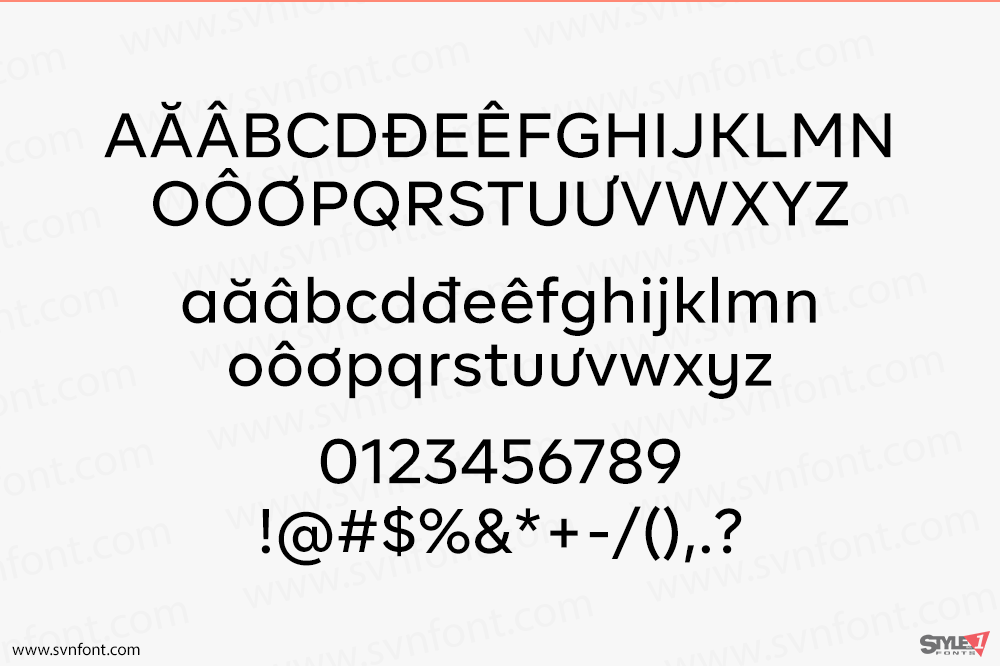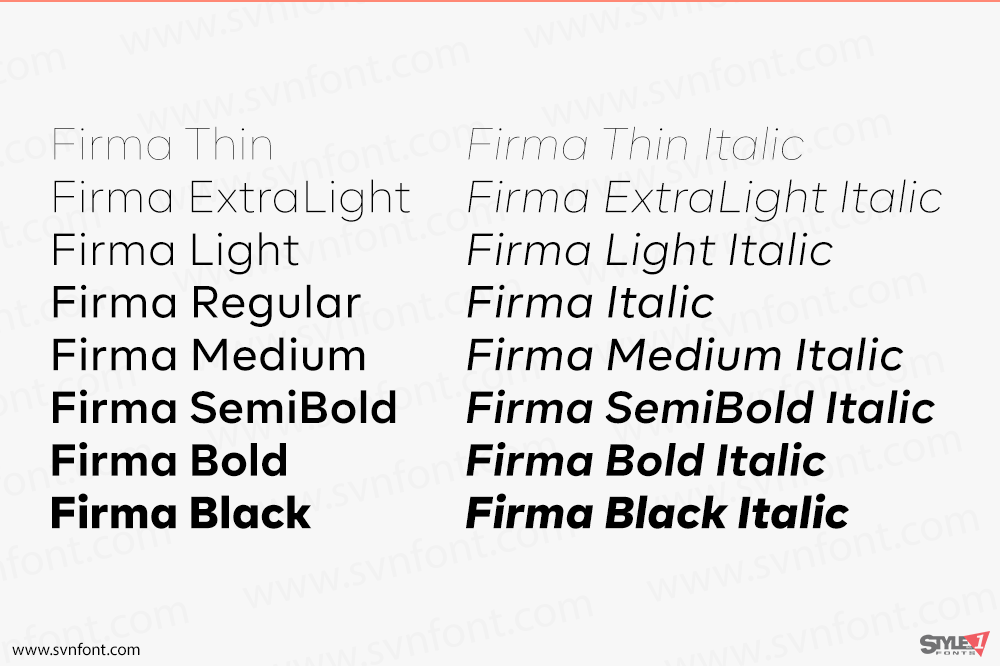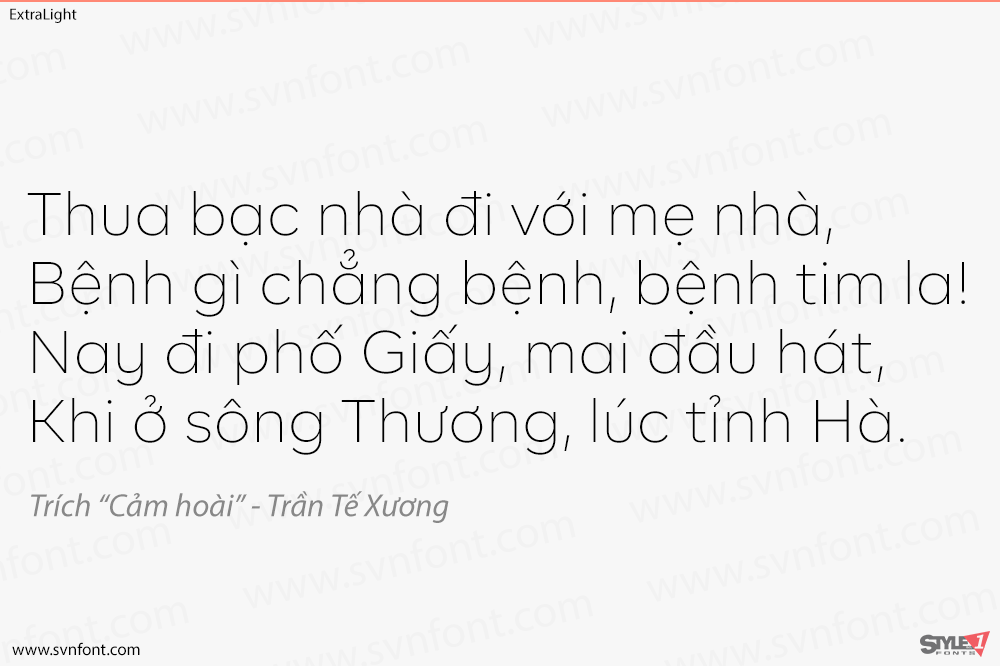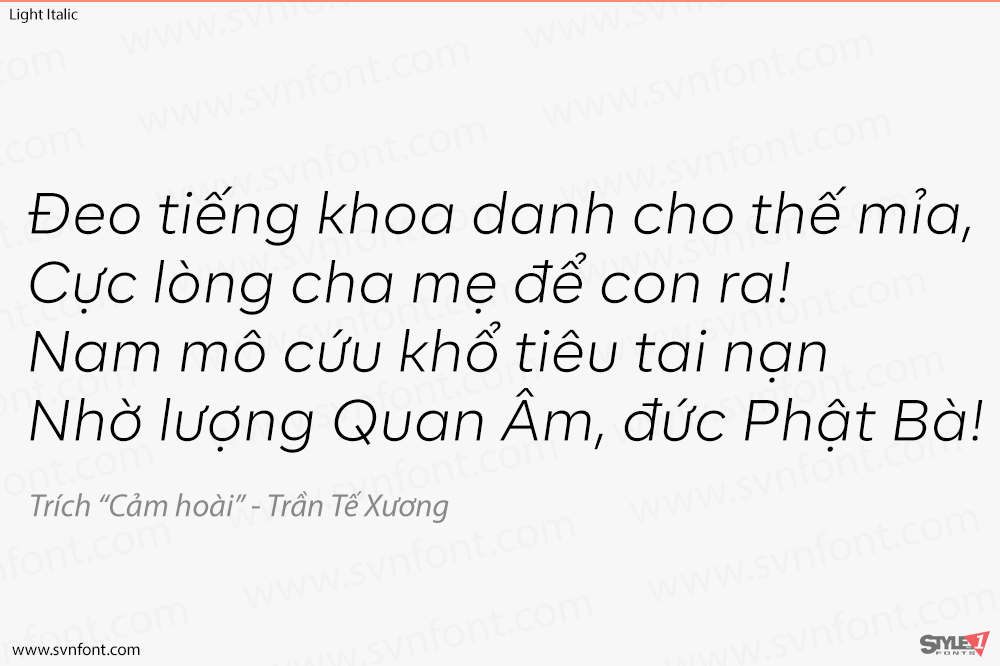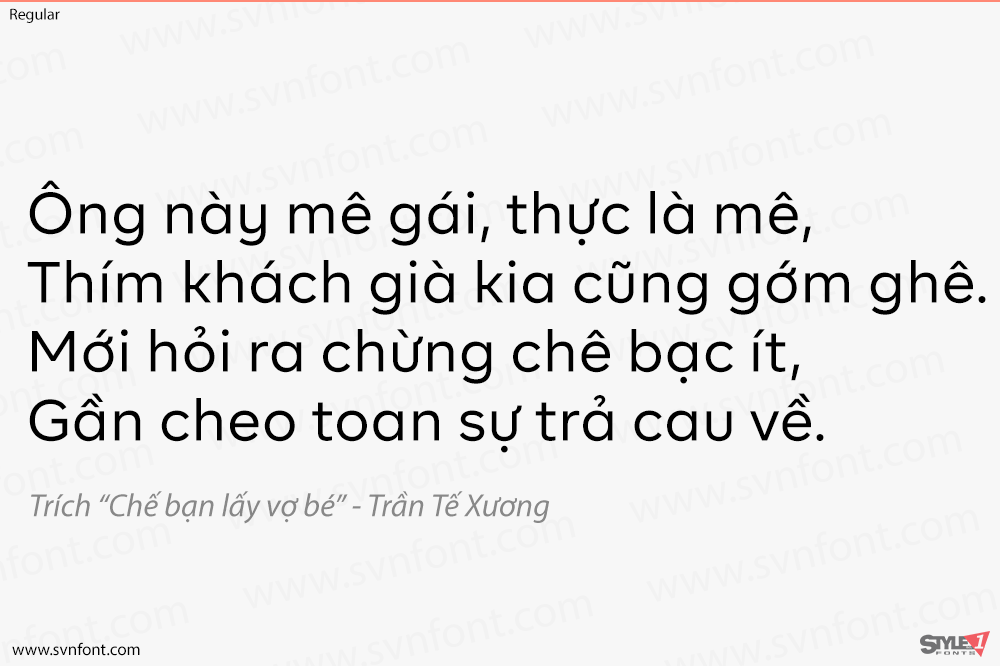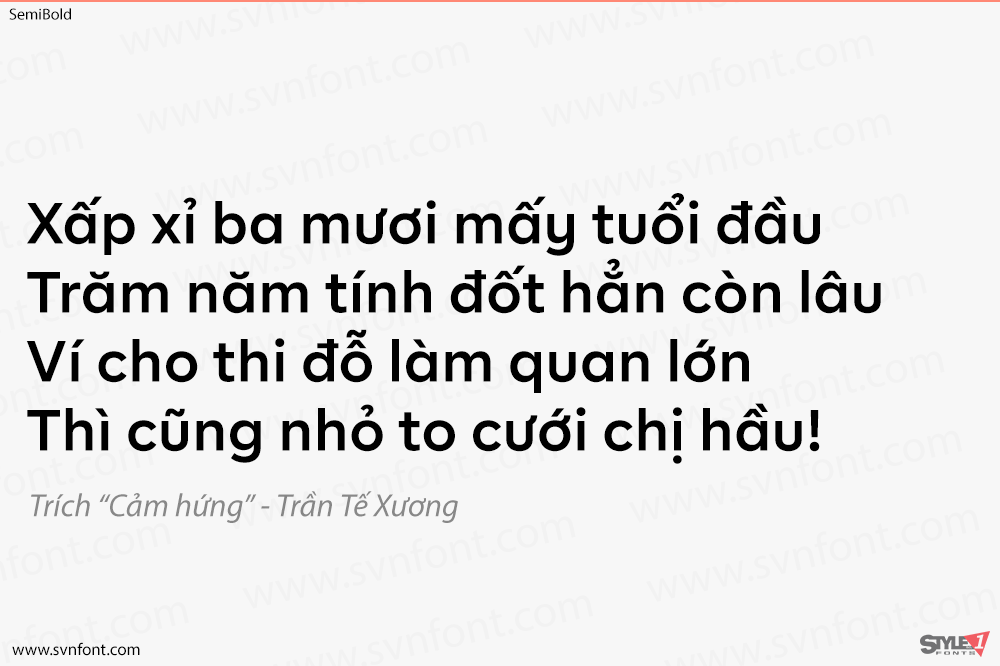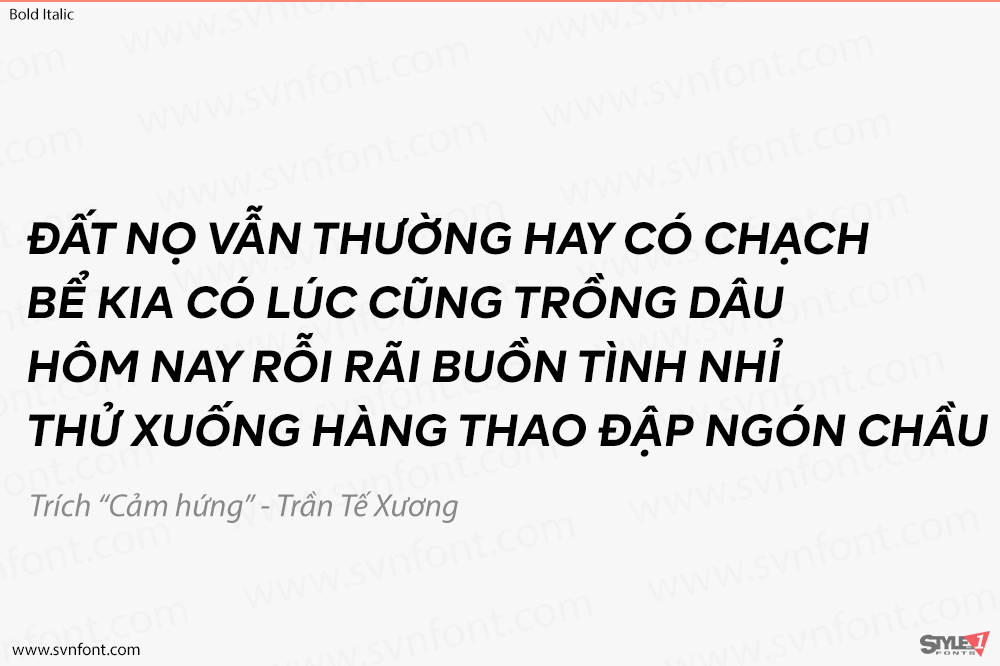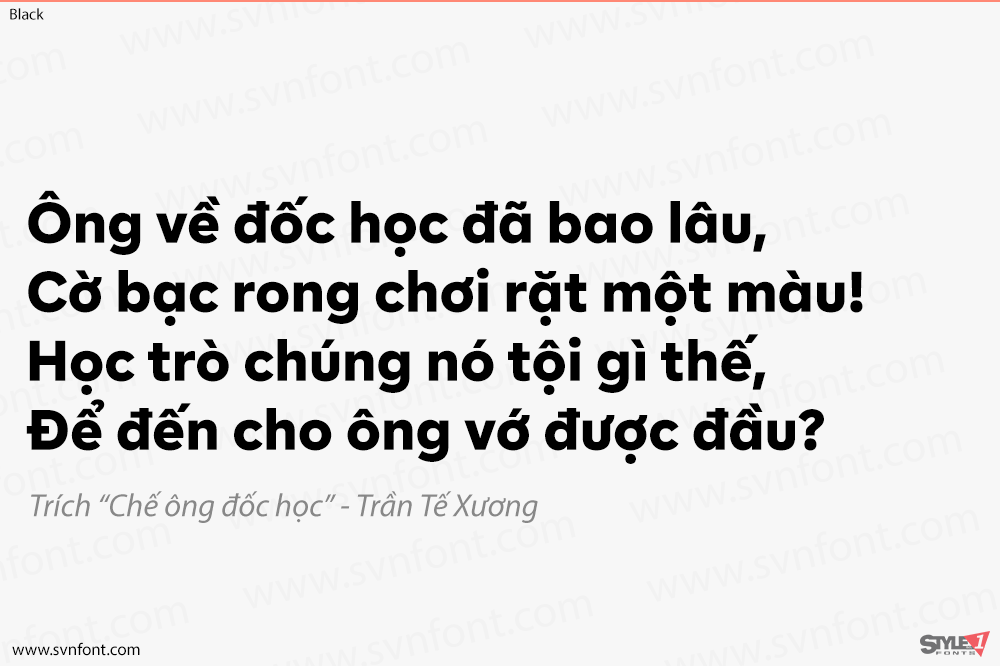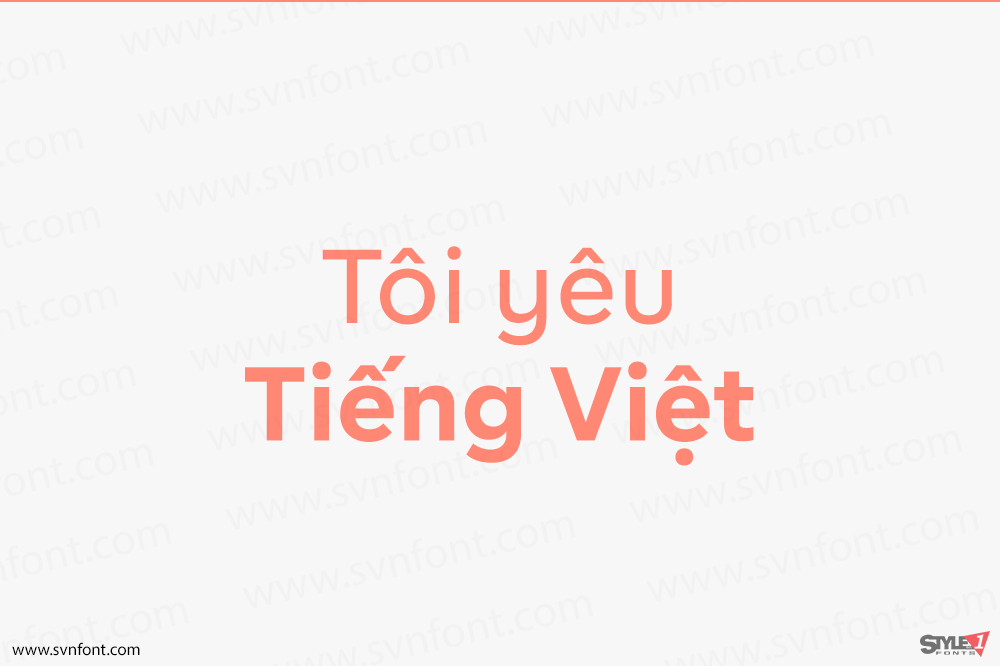
BR Firma là một font sans serif hình học bao gồm 8 độ đậm nhạt từ Thin đến Black cùng với kiểu chữ nghiêng (italics) tương ứng. Nó hỗ trợ bộ ký tự ‘Extended Latin’ bao phủ hơn 200 ngôn ngữ dựa trên tiếng Latin.
BR Firma cung cấp hỗ trợ kiểu chữ nâng cao với các tính năng như các dạng chữ nhạy cảm với chữ hoa/thường (case sensitive forms), phân số (fractions) và số không gạch chéo (slashed zeros). Nó đi kèm với nhiều bộ chữ số khác nhau và lý tưởng cho in ấn, quảng cáo, xuất bản, xây dựng thương hiệu, phần mềm và trò chơi, cũng như được tối ưu hóa cho thiết kế web và màn hình.
Nhà thiết kế: Christoph York
Nhà phát hành: Brink